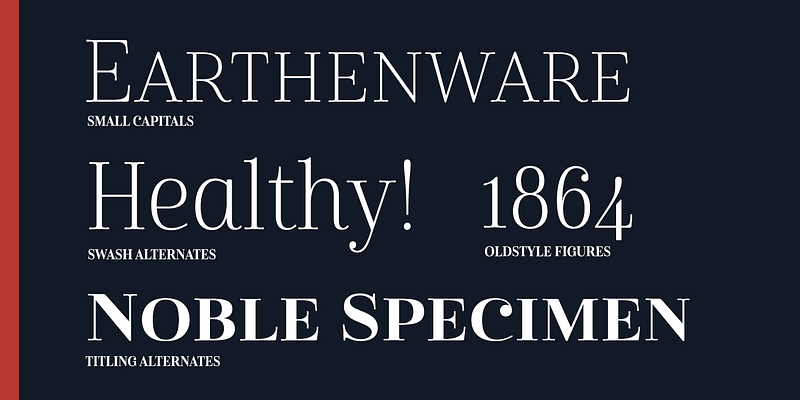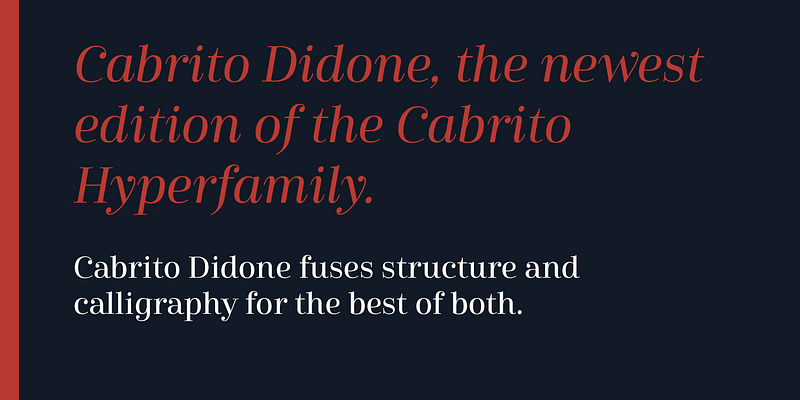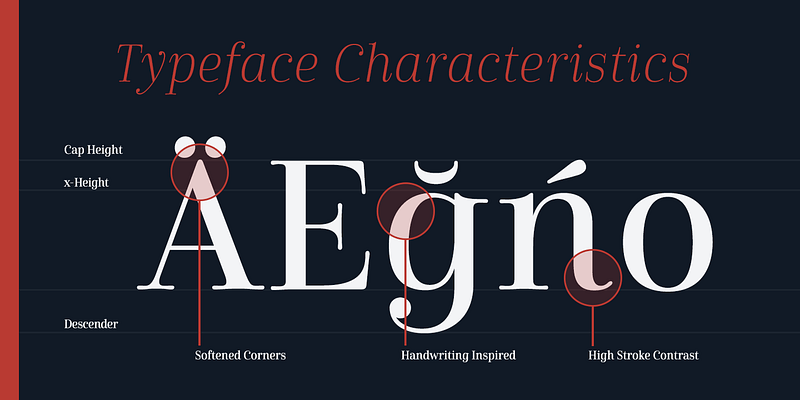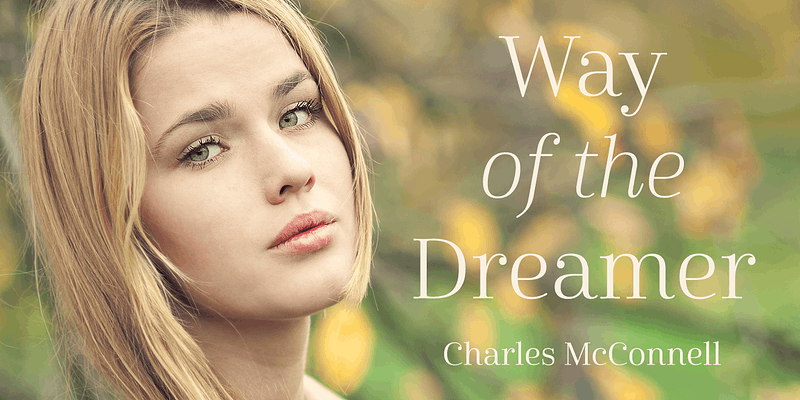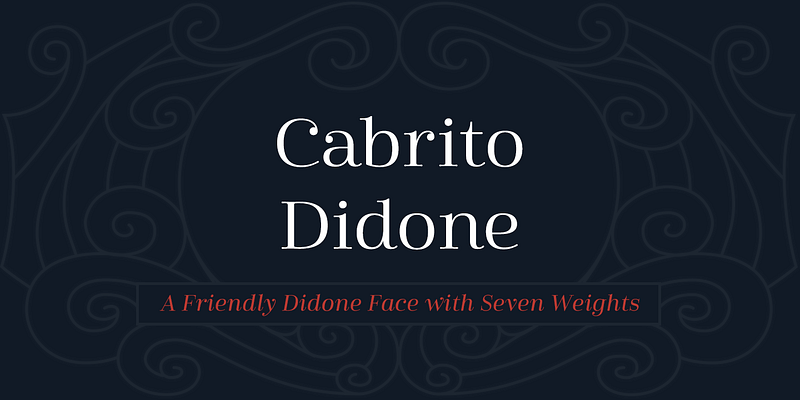
Cabrito Didone verbindet Struktur und Handschrift zu einem fließenden Gleichgewicht beider Merkmale. Einzigartige Serifen vermitteln den Eindruck, als ob die Tinte an den Spitzen, die mit einer scharfen Feder gezeichnet wurden, leicht aufläuft.